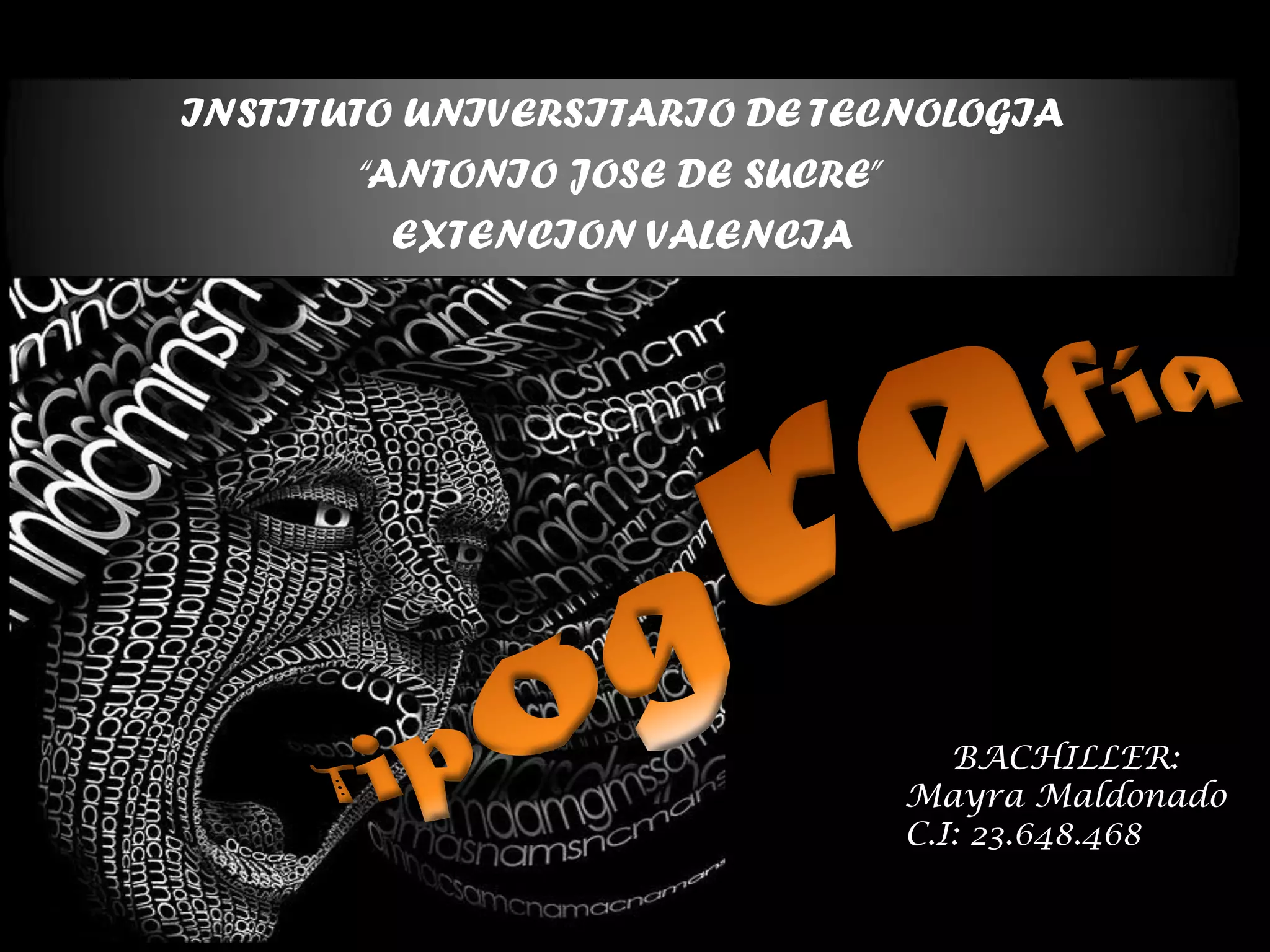
TIPOGRAFIA
Se conoce como tipografía a la destreza, el oficio y la
industria de la elección y el uso de tipos (las letras
diseñadas con unidad de estilo) para desarrollar una
labor de impresión. Se trata de una actividad que se
encarga de todo lo referente a los símbolos,
los números y las letras de un contenido que se
imprime en soporte físico o digital.
El origen de la tipografía
La tipografía tiene muy
antiguos orígenes, que están
relacionados con la caligrafía
y los manuscritos, que ya
eran usados antes del año
2500 A.C.
Durante toda la edad media
la "industria editorial" se
centraba en los monasterios
donde los libros eran
copiados a mano por monjes
especializados, llamados
copistas; esta labor se hacía
en el scriptorium, en donde se
copiaban los textos.
Historia de la tipografía
La primera escritura de la que se tienen registros
surgió en la Mesopotamia en el año 4000 AC y fueron los
sumerios quienes la idearon para identificar los productos en
el comercio existente entre los ríos. Entre estos dos surgieron
los Jeroglíficos egipcios (3100 AC) . Los asiáticos inventaron la
caligrafía ,pero en ese entonces el oriente estaba totalmente
aislado de occidente, los jeroglíficos y la caligrafía china eran
muy complejos.
Para luchar contra esa dificultad surge el alfabeto,
que es un conjunto de símbolos visuales (caracteres) que
representan sonidos (habla). Los cientos de signos que existían
se vieron reducidos a unos 20 o 30, lo cual era una verdadera
revolución.
En 1.450 se produjo uno de los
hechos más importantes para el
desarrollo de la Tipografía y de la
cultura humana: Johann Gutenberg
(1398-1468) inventa a la vez los
caracteres móviles y la prensa,
creando la imprenta. El primer
texto occidental impreso, la Biblia
de 42 líneas de Mazarino, sale en
1.456, al parecer de la imprenta de
Gutenberg.
Hacia el año 1500, el invento de
Gutenberg había tenido tan amplia
difusión, que en Europa ya existían
aproximadamente 1.100 imprentas
funcionando. En los países
germanos el estilo de letra más
usado era la fraktur
Anatomía del Tipo
Este término hace referencia a la
proporción que mantienen las
letras, sin embargo no hay que
olvidar que existe una variante y
una similitud entre todas las
familias tipográficas.
Los dos elementos principales en la
constitución de una letra son las
ASTAS y los REMATES. Respecto a
los contornos, encontramos internos
o externos. Entre las partes de las
letras se encuentran los brazos, la
cabeza, los remates y la cola.
Respecto a la alineación, se puede explicar de la siguiente
manera:
Para usar el quadratín en la construcción de las letras de
caja baja, se hace de la siguiente manera:
los términos de caja alta
y caja baja se originaron
al inicio del desarrollo de
la tipografía,
cuando tenían a cada
letra individual y
guardaban las
mayúsculas o de caja
alta en la parte superior
y las minúsculas o de
caja baja en la parte
inferior.
el quadratin es la caja de construcción de la letra. Es una
medida tipográfica que equivale a un cuadrado perfecto; la M
es la que se adapta de manera perfecta a esta medida.
Podemos usar el quadratín para la
construcción de las letras teniendo en
cuenta:
• M = Q
• V,Y,A = Q - 1a Caracteres abiertos
• W = Q + 2a
• B,D,H,K,N,P,R,T,U,X,Z = Q -
2a Letras regulares
• I = 1a
• C,G,Q,O,S,J,U = Q + 1/12a
• E,F,S,J,L = Q - 2 1/2ª
Q = 1 Quadratín
a = asta
Psicología y composición
del tipo
La tipografía está en todo lo que nos rodea,
aparece en la publicidad, en los comunicados
oficiales y en los mensajes personales. Sin embargo,
respetando unos mínimos de legibilidad, se pueden
usar todas estas características para transmitir
una emoción más general: es lo que se denominan
atmósferas textuales. Así, el tipo de letra de los
créditos de una película de terror, una cómica o un
drama serán muy distintos, porque todo comunica
y con la tipografía se envía un mensaje
independiente al del texto escrito.
Familias tipográficas
Existen multitud de familias tipográficas.
Algunas de ellas tienen más de quinientos
años, otras surgieron en la gran explosión
creativa de los siglos XIX y XX, otras son el
resultado de la aplicación de los ordenadores
a la imprenta y al diseño gráfico digital y
otras han sido creadas explícitamente para
su presentación en la pantalla de los
monitores, impulsadas en gran parte por la
web.
Romanas